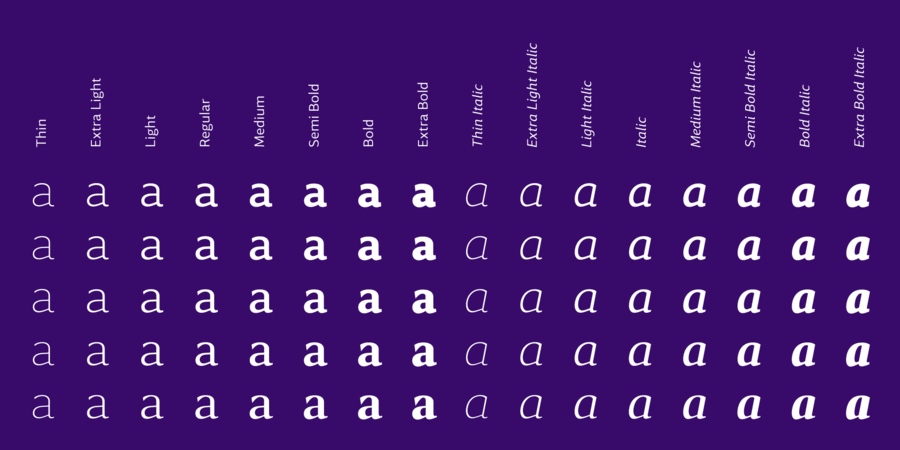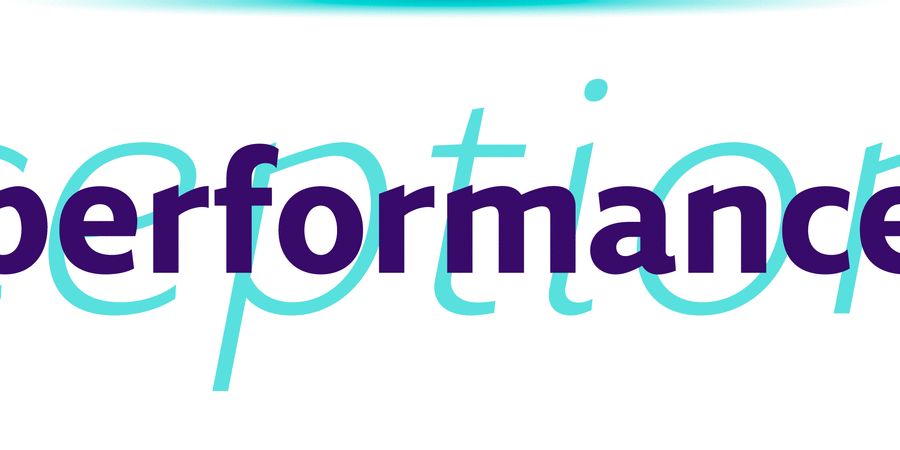
Accia – один з перших у світі шрифтів з варіативним переходом від гротеску до антиква. Діапазон значень осі жирності – від Thin до Extra Bold, а по осі зарубок – від Sans до Forte. Accia спроектована так, щоб її можна було використовувати в будь-якій точці простору дизайну, а її різні варіанти чудово працюють разом як нескінченно гнучка типографічна система. Гарнітура містить 879 гліфів із підтримкою кількох мов на основі латинки та кирилиці, разом із додатковими наборами цифр і розділових знаків, капітеллю, лигатурами й іншими поширеними функціями OpenType. Accia також доступна у вигляді 5 окремих шрифтових сімейств: Accia Sans, Accia Flare, Accia Piano, Accia Moderato та Accia Forte. Гарнітуру розробив Андрій Константинов у студії Mint Type в 2021 році.
Асоціації з сімейством шрифтів Accia VariableОсобистість і характер гарнітури:
витончений, модний, якісний, культурний, добірний, благородний, гармонійний, елітний, дорогий, розкішний, красивий, майстерний, художній, знаменитий, оригінальний, комільфо, багатий, міський, гострий, виразний, характерний, динамічний, аристократичний, історичний, світський, цікавий, рівний, діловий, космополітичний, технічний, сучасний, точний, логічний, освічений, стійкий, формальний, серйозний, розумний, твердий, чіткий, різкий, колючий